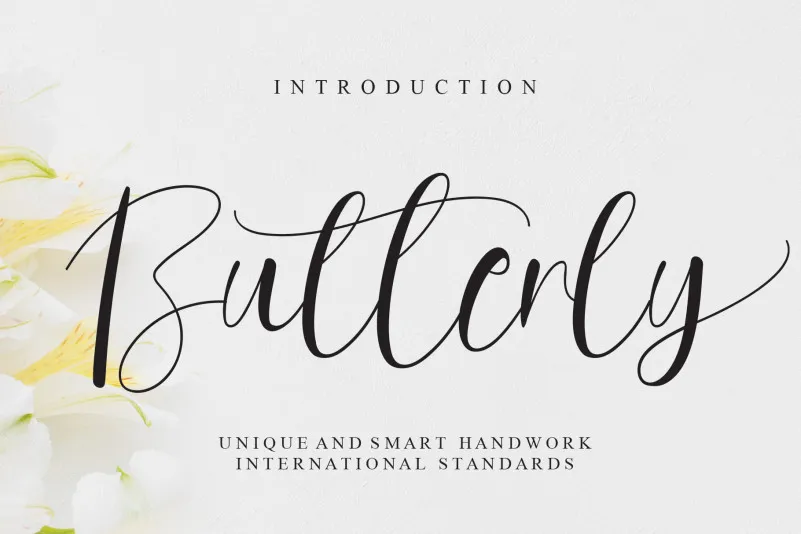
Butterly Font
Esta elegante fonte à mão escrita traz uma aparência alegre e acolhedora que certamente enriquecerá qualquer projeto. Seja para adicionar ao seu logotipo, marca de água, fotografias ou etiquetas, ela proporcionará um toque delicado de escrita manual que deixará o seu trabalho ainda mais personalizado e encantador. Inspirada no design dos bichos da serpente, a Butterfly Font é uma escolha ideal para aqueles projetos onde um pouco de charme adicional seria bem-vindo. Com ela, você pode criar mensagens sutis e memoráveis que se combinam perfeitamente com o estilo criativo da fonte à mão escrita da CreativeLetter. Aproveite a oportunidade de adicionar uma pitada de originalidade e delicadeza a qualquer projeto gráfico que precise de um toque especial.